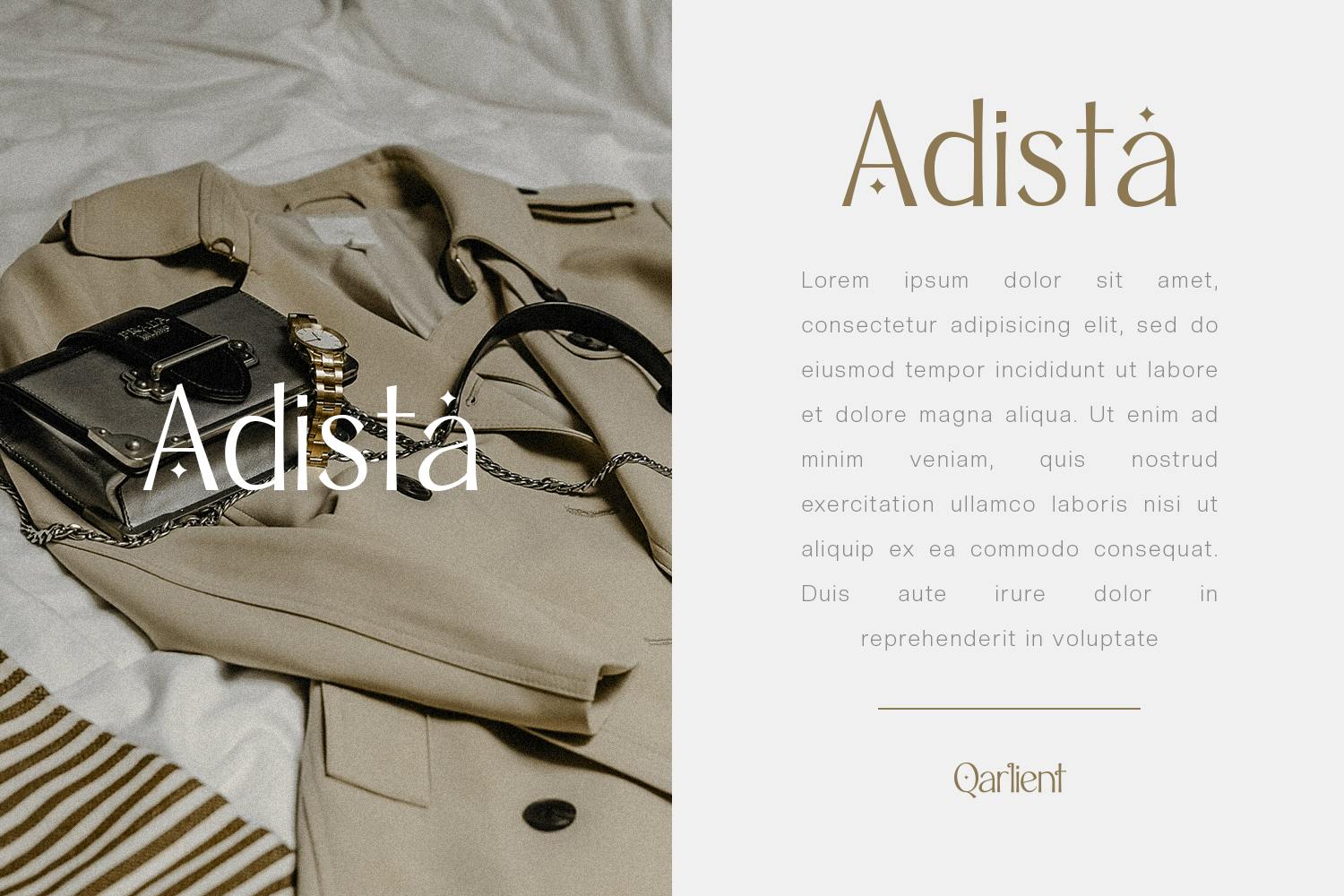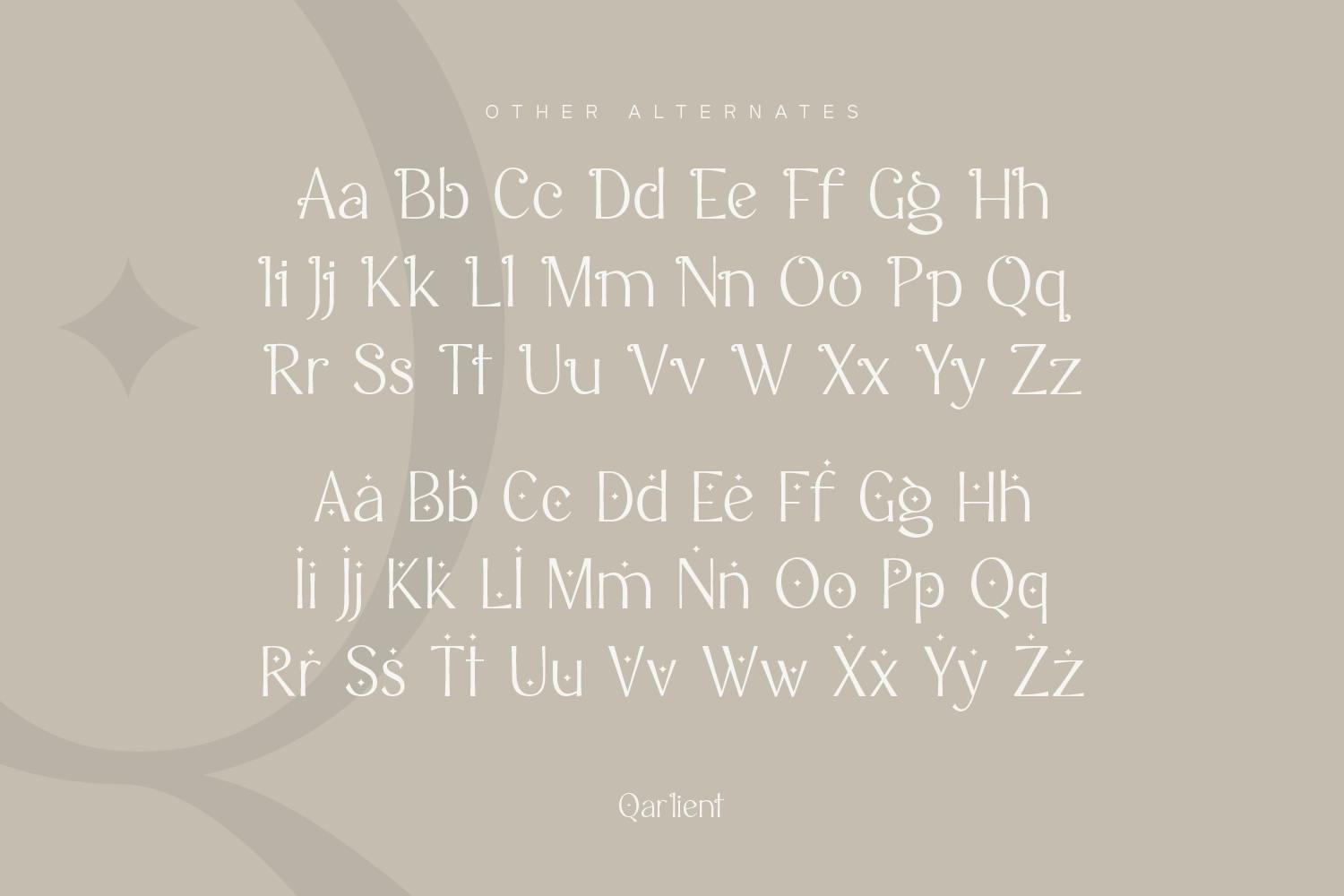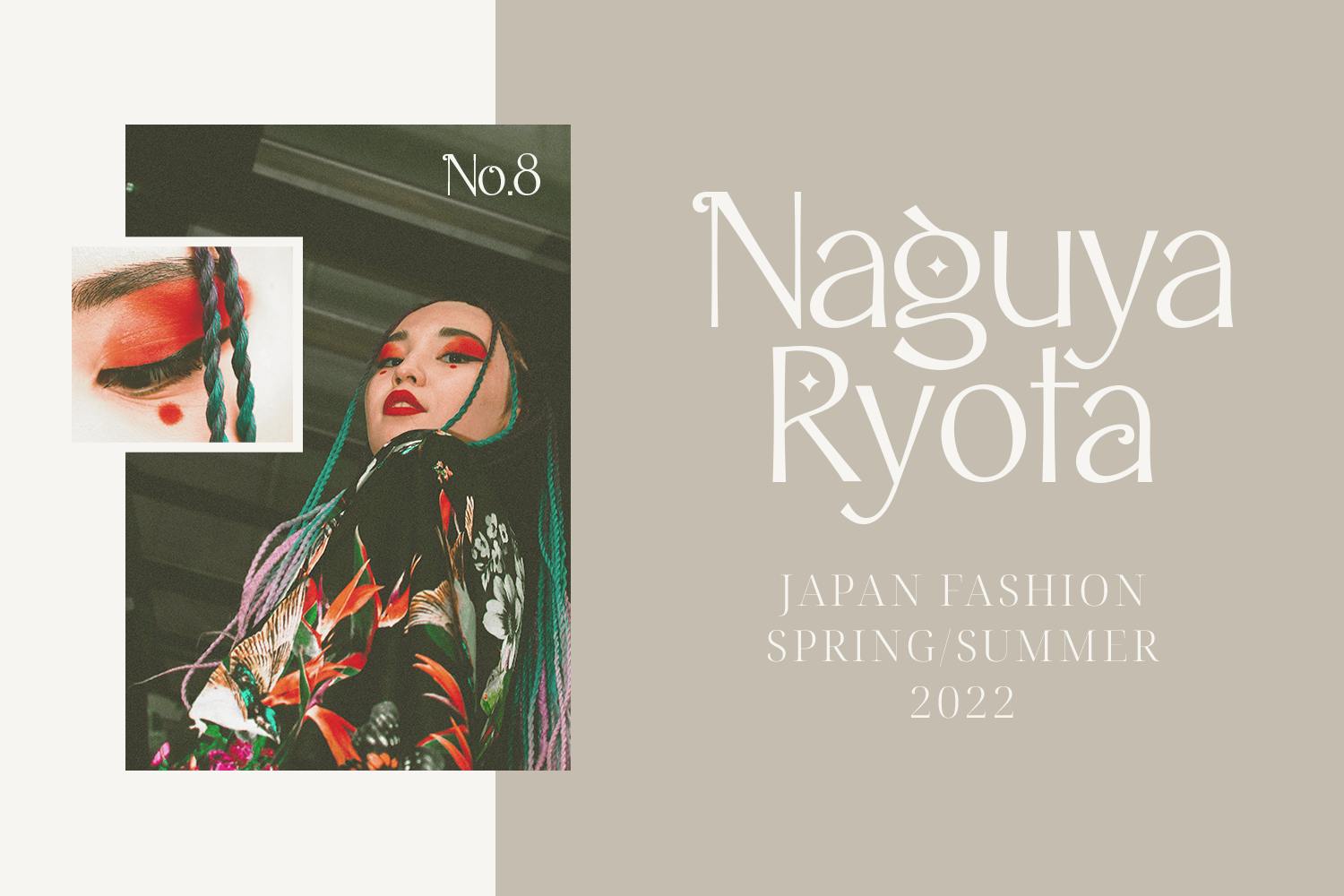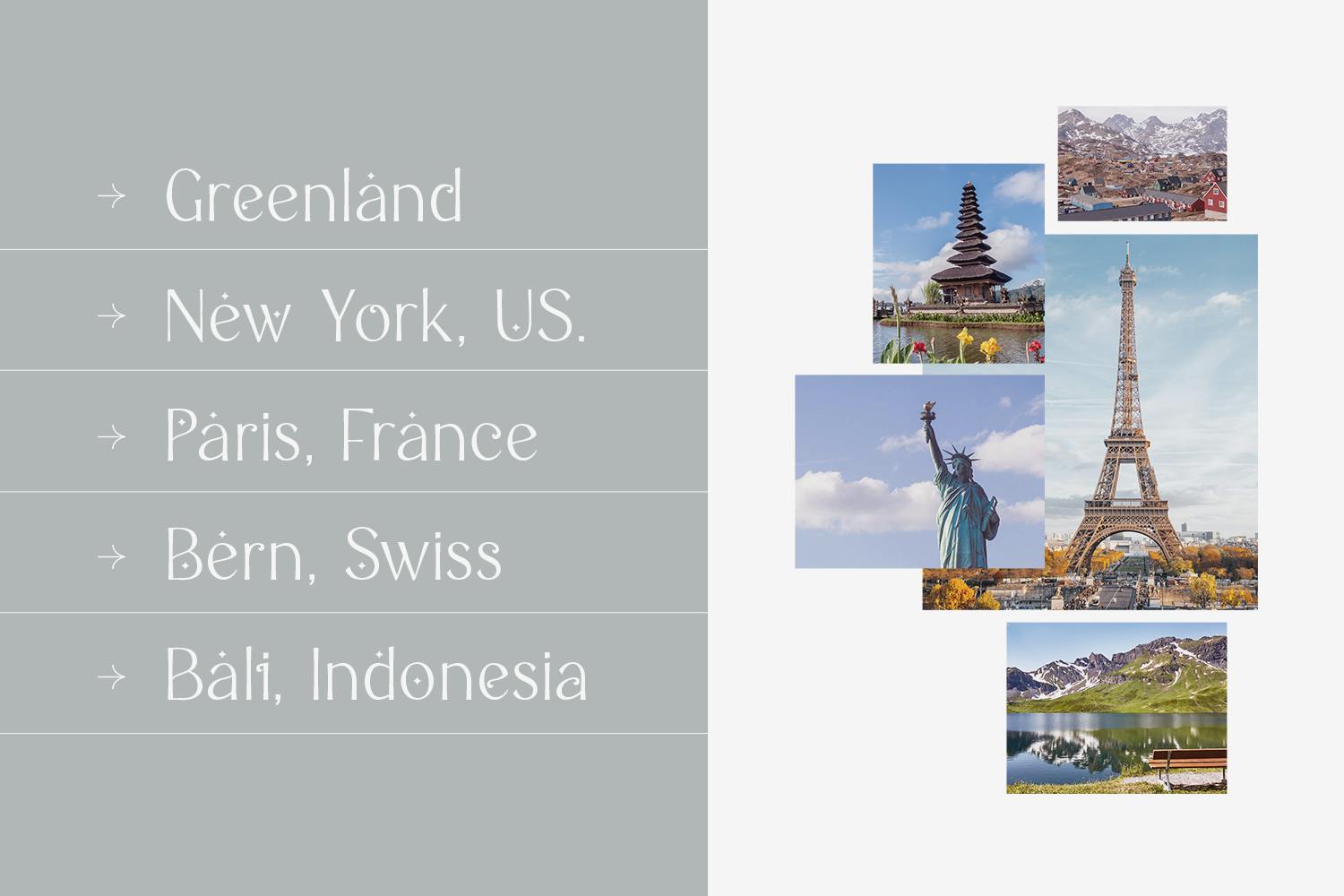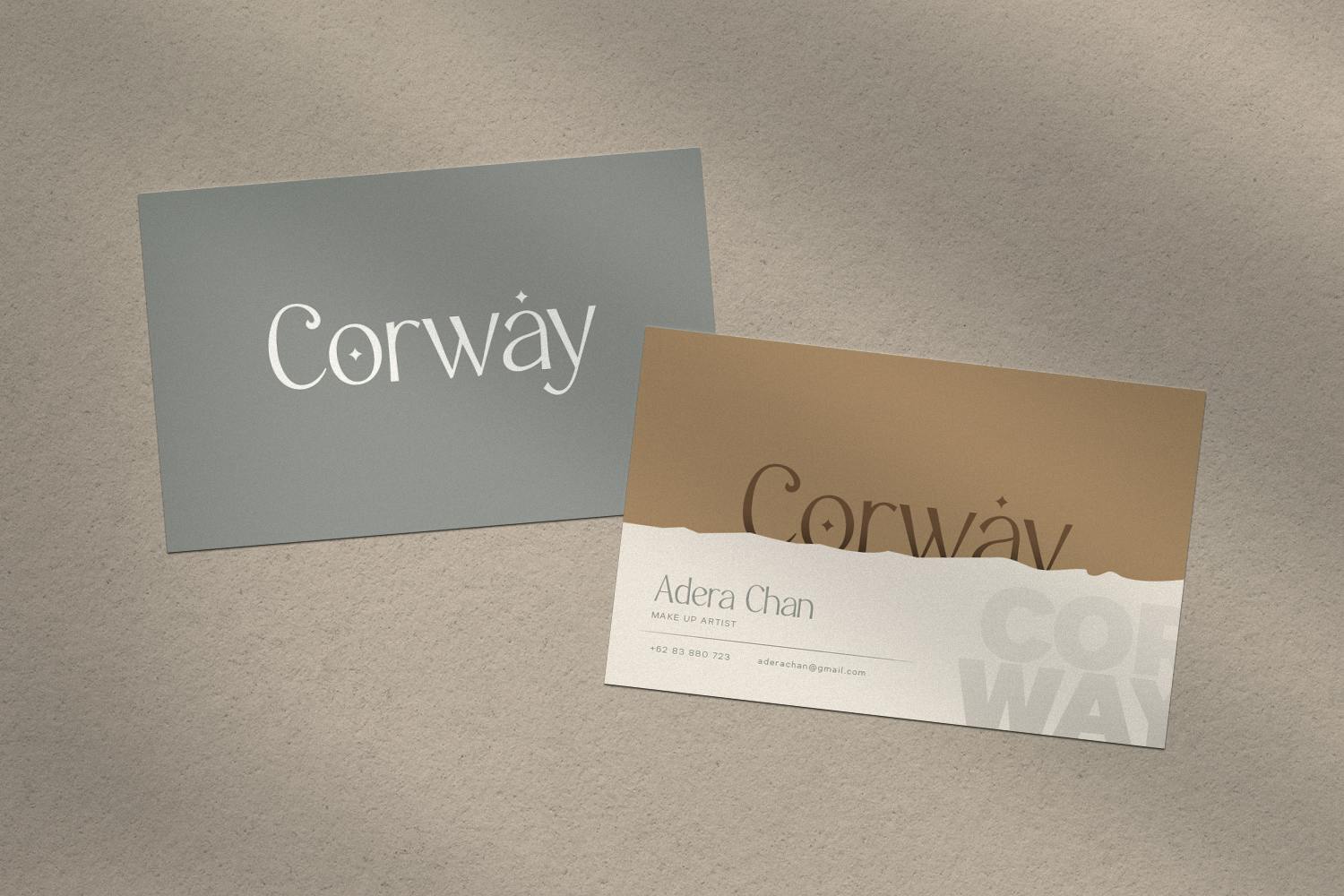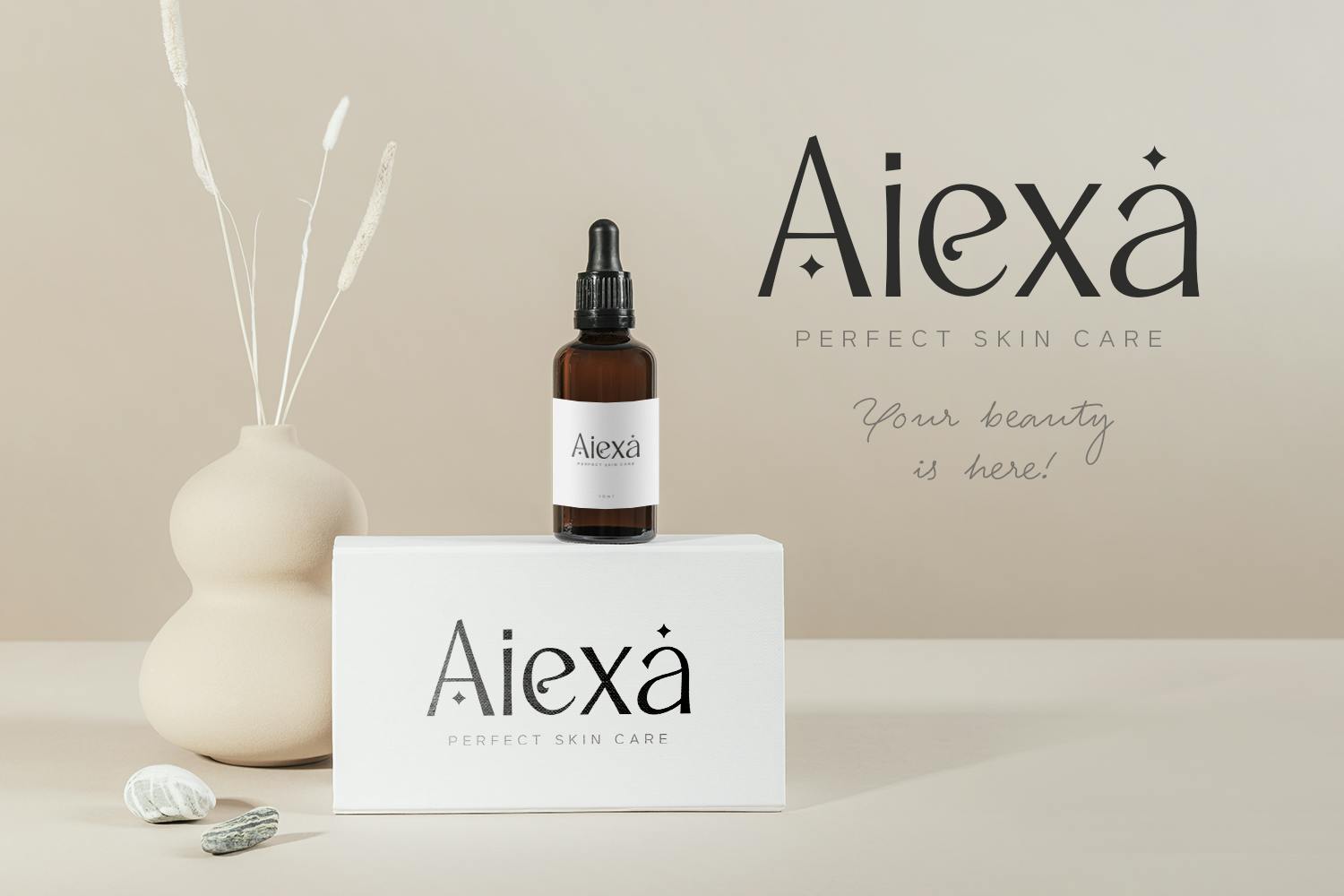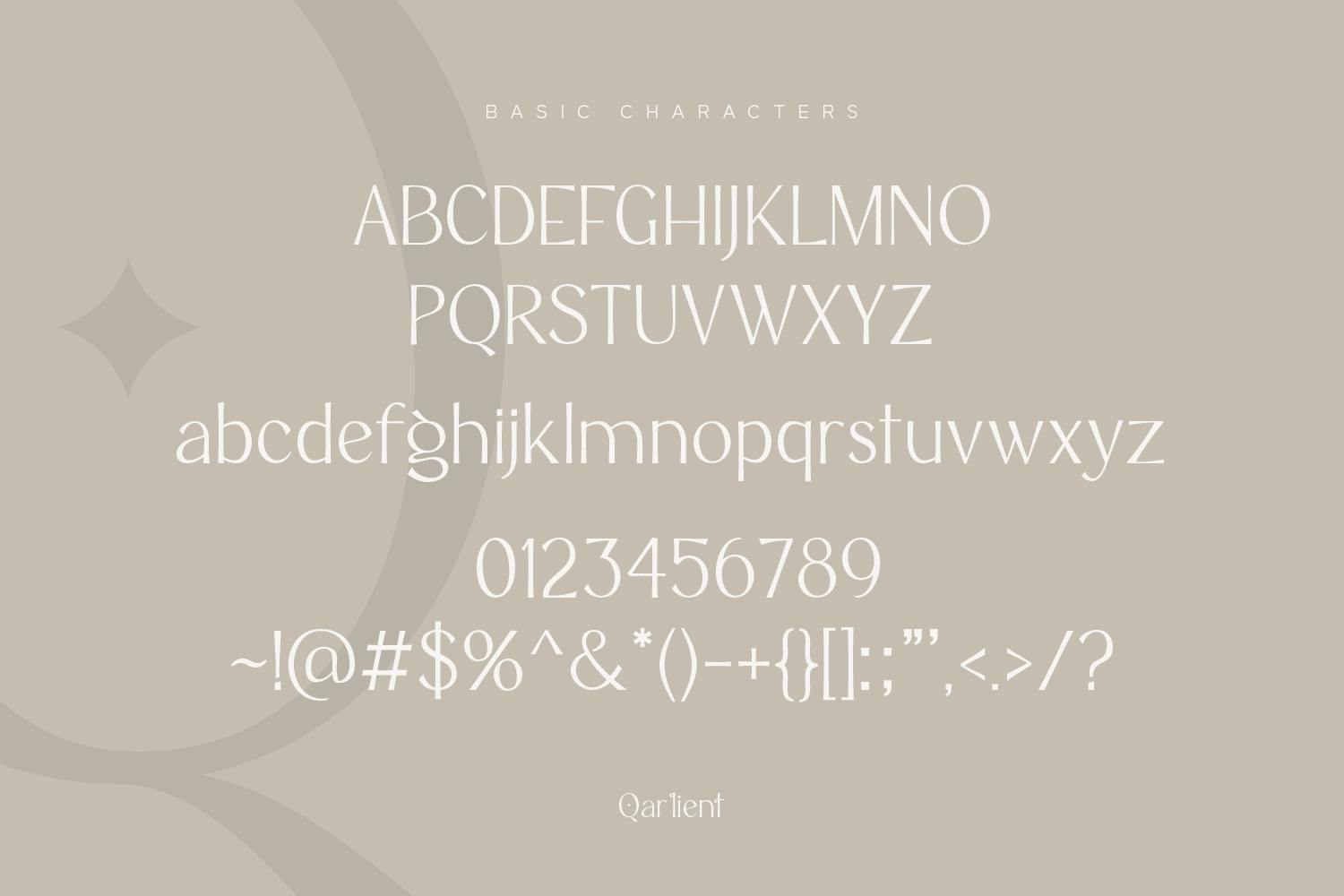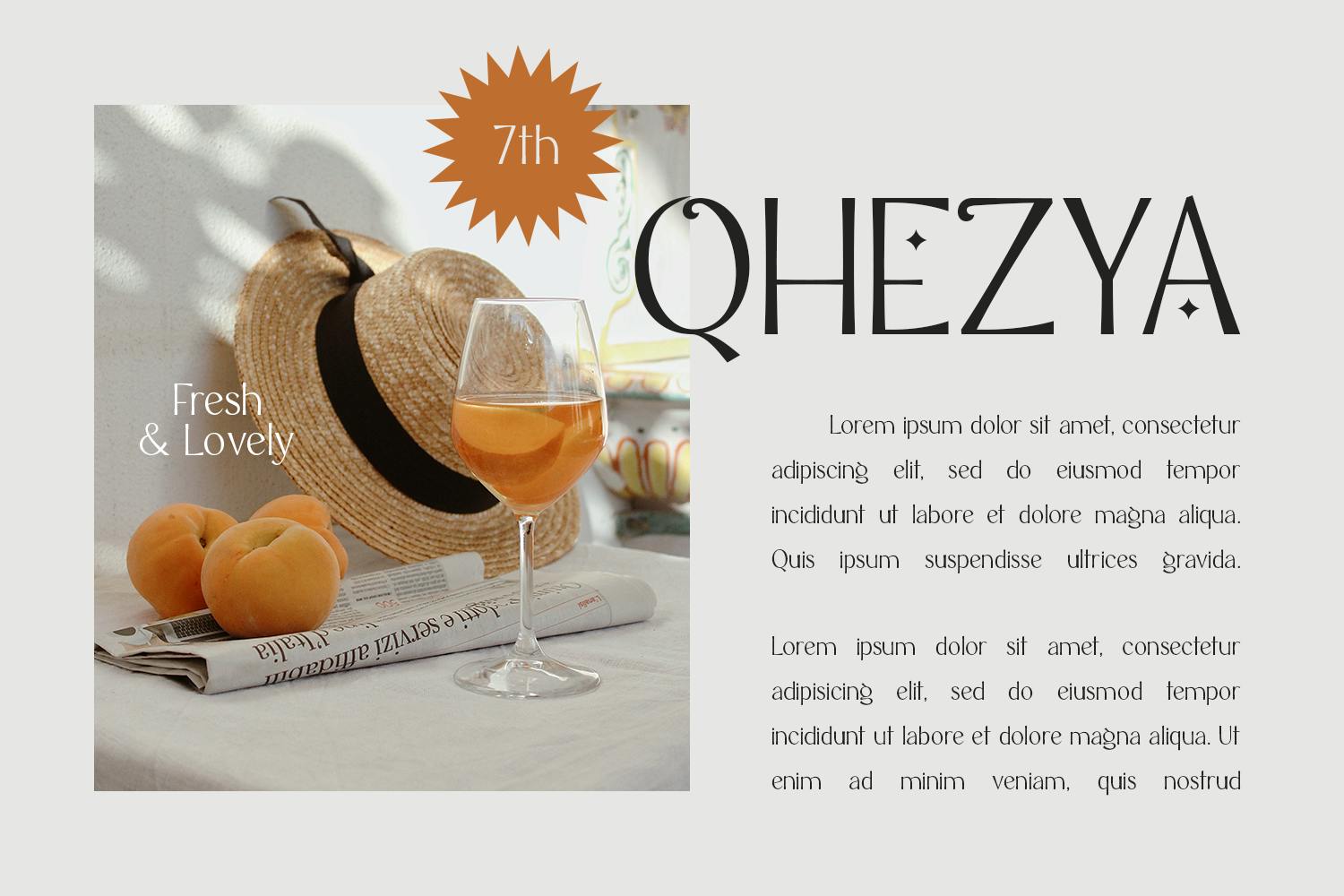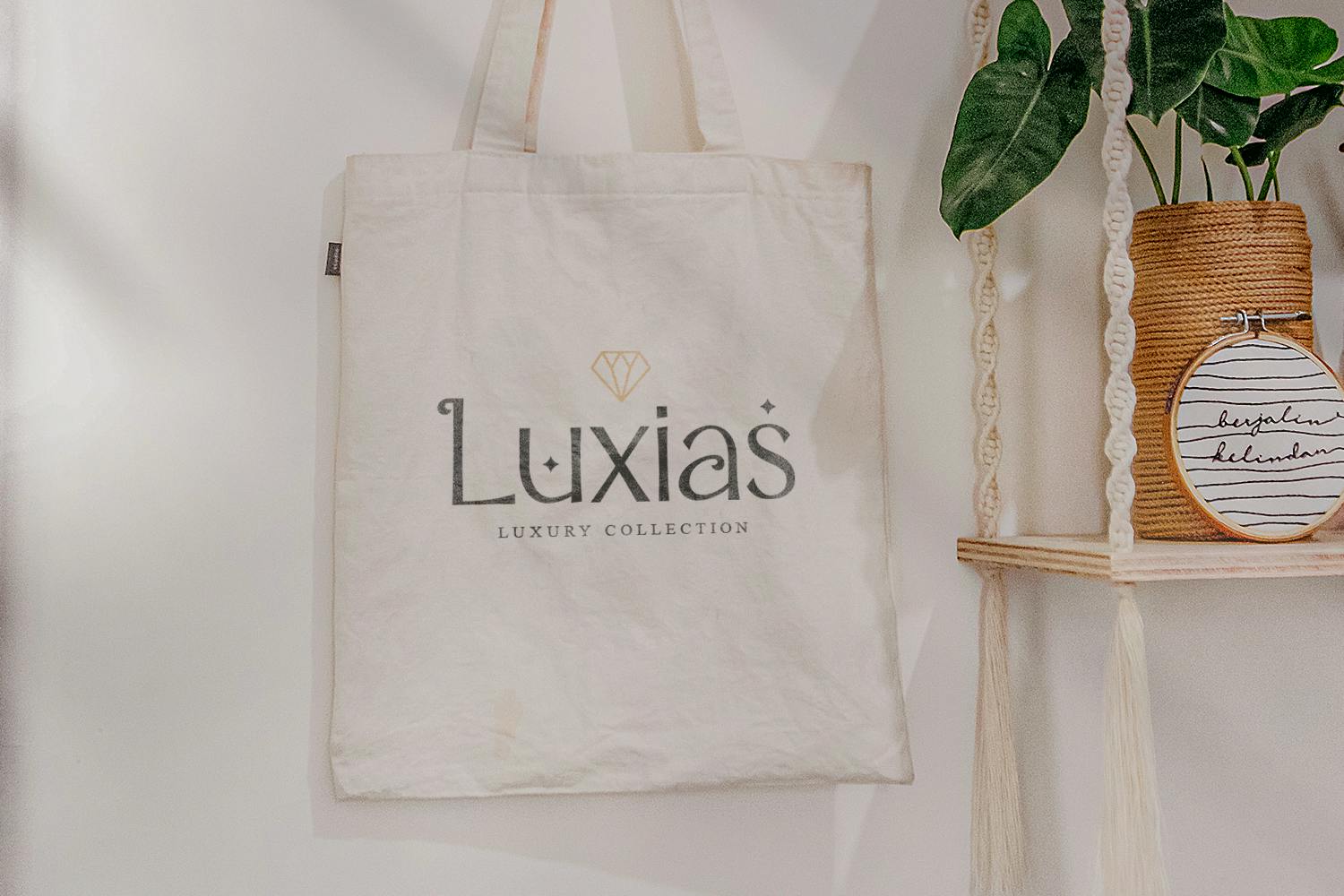
معرفی Qarlient - یک فونت مدرن سنس سریف
فونت Qarlient یک فونت مدرن و قدرتمند سنس سریف است که با تازگی، ظرافت و ظاهر منحصر به فرد خود، توجه را جلب میکند. این فونت با الهام از سبکهای باستانی، کلاسیک و مدرن طراحی شده است و برای ایجاد ظاهری ساده، مدرن و شیک مناسب است. تنوع زیبایی و لوکسی که این فونت دارد، آن را بسیار چندمنظوره میکند. این ویژگی باعث میشود تا هر طراحی برند یا لوگو به شکلی منحصر به فرد به نظر برسد. فونت Qarlient برای مجلات، رسانههای اجتماعی، پوستر، کارت ویزیت و بسیاری دیگر از پروژههایی که نیاز به لمسههای خاص دارند، ایدهآل است.